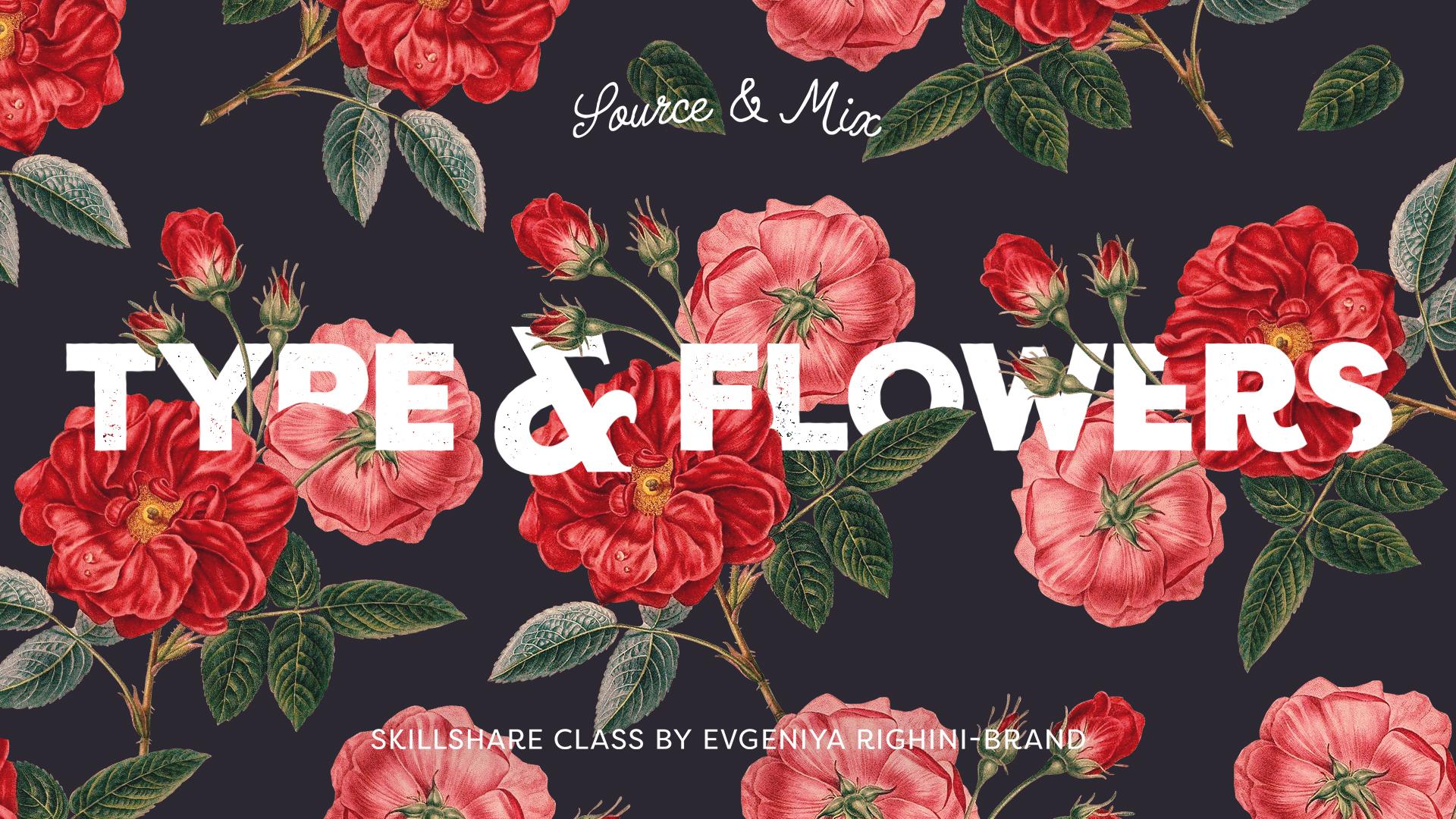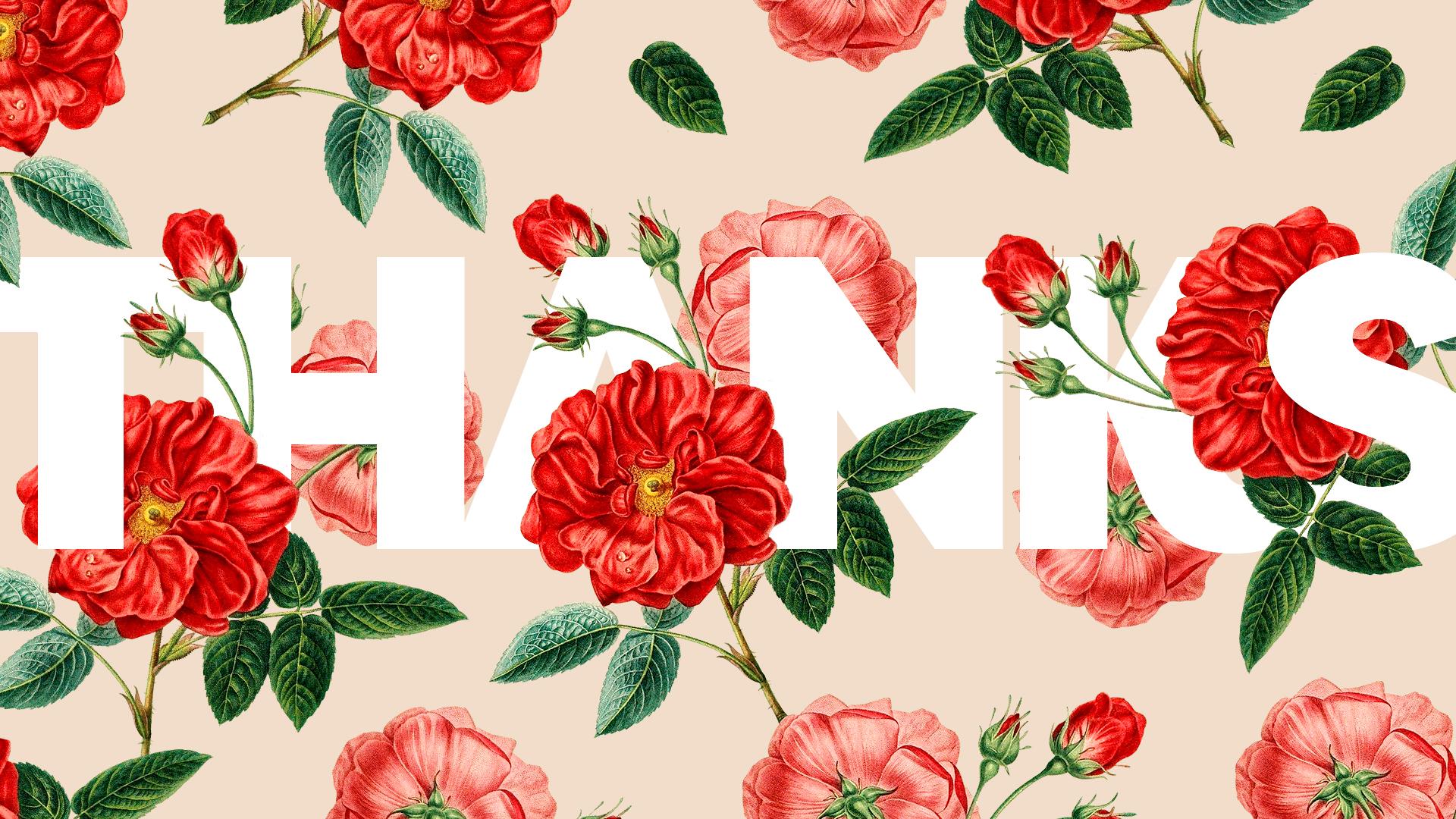
1. Aperçu du cours: Type audacieux et simple combiné avec de belles illustrations florales ou botaniques. Je parie que vous en avez vu beaucoup ces derniers temps sur des cartes, des
vêtements, des articles de papeterie de mariage et des affiches. C' est un moyen très simple mais très efficace de créer des designs
élégants avec un sens de valeur et de sophistication. C' est Eugenia de Attitudes Creative et dans cette classe, je vais passer par le processus de combinaison d'illustrations botaniques vintage trouvées de ce type pour créer des designs captivants qui peuvent être utilisés dans un large éventail de projets, de cartes de vœux personnelles, papeterie de
mariage ou décoration de fête à tout matériel marketing et identité visuelle. Cette classe couvre une nouvelle série de techniques Photoshop telles que l'utilisation des masques de calque, ajustements de
couleur et la toute nouvelle fonctionnalité de type de correspondance Photoshop. Je serai très heureux de voir ce que vous pouvez créer. Rejoignez-moi dans cette classe pour faire quelque chose de branché, pour célébrer l'été et la belle typographie.
2. Approvisionnement et coupe: Avant de commencer, parcourez et trouvez des images inspirantes. Si vous voulez vérifier mon tableau Pinterest, tapez des fleurs pour commencer. Ensuite, trouvez quelques belles images source que vous pouvez utiliser dans votre conception. Tout ce qui est floral ou botanique peut très bien fonctionner dans cette classe. Ça n'a pas besoin d'être une fleur. Il peut s'agir de feuilles, de branches ou de fruits ou de baies. J' aime vraiment l'apparence de cette rose donc c'est ce que je vais utiliser. Je reçois des images de la biodiversité et si vous ne savez pas où trouver des images, consultez la liste des ressources de cette classe, et regardez ma précédente classe sur les collages numériques à partir d'illustrations d'encyclopédie vintage, où j'ai montré un gamme de sources de ces images. Assurez-vous que l'image que vous souhaitez utiliser dans votre conception n'est pas protégée par le
droit d'auteur et téléchargez la plus grande taille disponible. Maintenant, je vais ouvrir l'image téléchargée dans Photoshop et re-enregistrer comme elle est tout de suite dans le dossier source de ce projet. Ce fichier que je vais garder en tant que fichier source. Donc, j'ai toujours le fichier original au cas où j'aurais besoin de revenir en arrière et de faire autre chose avec. Ensuite, je vais le recevoir dans l'autre dossier où je vais garder la découpe. Je vais l'enregistrer au format PSD parce que je voulais de la transparence. Je vais garder le même nom de fichier pour l'instant, et je vais intégrer le profil de couleur et je vais cliquer sur « Enregistrer ». Maintenant, ce que je dois faire est de couper la rose de son arrière-plan. Je vais utiliser l'outil de lasso polygonal. Mais si vous voulez utiliser une autre méthode, vous pouvez le faire. Si vous ne savez pas comment découper les choses, revenez à ma classe précédente sur les collages numériques où je couvre et montre une gamme de différentes façons de découper les choses dans Photoshop. Avant de commencer à couper, je veux dupliquer le calque. Donc, je l'ai juste au cas où et je vais créer une autre couche ici avec une couleur vive afin que je puisse voir comment mes boutures fonctionnent. Maintenant, je vais zoomer assez près et commencer à couper. Lorsque j'ai coupé mon image, j'ai besoin de dupliquer ce calque quelques fois et de séparer quelques éléments sur différents calques pour pouvoir masquer
facilement les choses et utiliser un peu dispersé autour de mon dessin. Je veux donc séparer cette fleur, quelques bourgeons et quelques feuilles. Maintenant, je vais renommer rapidement toutes les couches
afin de pouvoir naviguer rapidement dans mon fichier et l'enregistrer. Après avoir séparé ma rose en éléments séparés, je vais enregistrer ce fichier en tant que fichier maître et je n'y apporterai plus de modifications. Je vais garder le maître dans sa taille d'origine, mais pour cette classe, je veux redimensionner cette image. Donc, je vais aller au menu, taille de
l'image, et je vais changer la résolution à 300 dpi. Je vais continuer à rééchantillonner pour préserver les détails. Je vais changer les unités en centimètres et changer la taille de mon image. Je n'ai pas besoin qu'il soit si grand parce que le design final va être beaucoup plus petit. Je vais donc descendre à 20 centimètres de largeur pour avoir une image de bonne qualité. À ce stade, assurez-vous de ne pas écraser votre fichier maître, mais plutôt d'enregistrer des couches d'éléments individuels sous forme de fichiers séparés. Donc, je vais passer par les calques un par un, supprimant tout ce dont je n'ai pas besoin et en enregistrant chaque élément dans un document PSD distinct. Maintenant, je suis prêt à commencer à travailler sur mon design. Si vous avez plus d'une image source à couper, passez par le même processus, puis passez à l'étape suivante.
3. Agencement des éléments: Après avoir découpé toutes les illustrations que vous souhaitez utiliser dans votre conception, il est temps de commencer à les assembler toutes. Créons un nouveau fichier dans Photoshop. Puisque pour ce projet de classe, nous allons créer une carte de vœux, nous devons le garder à l'esprit lors de la configuration du document. tailles standard des cartes de vœux peuvent varier légèrement d'un pays à l'autre, mais en général, elles conservent quelque part environ six ou cinq points si elles sont grandes ou peuvent être carrées selon le côté le plus long du format A6. Étant donné que nous sommes tous dans différents pays, je suggère que vous décidiez de la taille pour vous-même, fonction de ce qui est utilisé dans votre pays. Je vais accepter les tailles standard A pour l'instant. Je suis généralement assez débrouillard quand je travaille et je pense à l'avance sur la façon dont je peux utiliser ce sur quoi je travaille. Maintenant, sachant que je travaille réellement sur la carte, je vais créer un fichier gratuit à la place afin que je puisse aussi utiliser ce travail pour quelqu'un d'autre. utilisation des formats A est également assez bonne parce que je peux assez facilement l'échelle
proportionnellement mon travail vers le bas pour atteindre la taille A6 désirée de la carte finale. Je vais utiliser le mode couleur RVB parce que je vais télécharger dans mon travail juste société six et c'est ce qu'ils utilisent, mais si vous voulez utiliser CMJN et imprimer votre travail professionnellement, allez-y. Cliquez sur « OK » et sauvegardons ce fichier tout de suite. Je vais le mettre dans mon dossier de développement, le renommer, assurez-vous que ce format NPSD et cliquez sur Enregistrer. Maintenant, je peux commencer à placer ma carte dans ce fichier. Vous pouvez le faire comme vous le voulez, et je vais placer des fichiers liés afin que je vais passer par toutes mes découpes un par un et les placer dans mon document. Assurez-vous de cliquer sur « Entrée » pour placer l'image. J' ai tous les éléments dont j'ai besoin dans un seul fichier. J' ai les règles complètes et tous les éléments individuels en tant que couches séparées. Ils sont tous au même endroit que sur leurs règles d'origine, ce qui sera très pratique à la prochaine étape de masquage. Je vais regrouper tous les éléments individuels et les cacher parce que je n'en ai pas besoin pour le moment, puis je vais commencer à travailler sur la composition globale de la carte. Les rôles sont en fait assez petits par rapport
au format global et c'est bon car il sera plus facile masquer les choses sinon le type serait
trop caché par les éléments de la rose ou vice versa. En termes de composition globale, vous pouvez faire ce que vous voulez. Vous pouvez avoir un seul élément sur un fond coloré, vous pouvez avoir une image de taille supérieure si vous formater est comme
ça ou vous pouvez dupliquer vos images et les disperser sur toute la toile. Vous décidez de l'apparence de votre carte. Ça a l'air sympa. Maintenant, je veux changer l'arrière-plan. Je vais aller chercher quelque chose de gentil et [inaudible], qui fonctionnera bien avec ces fleurs pour l'instant, et j'y reviendrai plus tard dans tous les cas pour finaliser mon design. Vous pouvez utiliser tous les raccourcis de suppression pour remplir le calque avec la couleur de premier plan définie dans le panneau Outils ou utiliser l'outil de seau de peinture. Maintenant, je peux commencer à penser à comment je peux ajouter du type à cette composition.
4. Ajout d’un type: Retournez à votre recherche et décidez de l'écriture que vous voulez avoir sur votre carte. Ça peut être n'importe quoi. Vous pouvez inclure seulement quelques mots pour définir l'ambiance. Vous pouvez utiliser un devis. Vous pouvez écrire, félicitations, joyeux anniversaire ou merci. Vous pouvez écrire le nom ou les initiales de quelqu'un. C'est à vous de décider. Je vais aller pour quelque chose de simple et polyvalent. Maintenant, je dois rendre ma typographie agréable. La première chose que je vais faire est en fait de définir la couleur de mon texte, quelque chose que je peux bien voir et travailler avec, mais ce n'est peut-être pas la couleur finale que je vais utiliser tout de suite. Ensuite, j'ai besoin de choisir de belles polices de caractères ou polices de caractères. Si vous n'êtes pas très confiant de travailler avec le type, consultez ma première classe dans la série de topographie de mastering, qui couvre les principes de base de la création de compositions typographiques visuellement attrayantes, sélection et l'appariement de polices de caractères, et les paramètres disponibles dans les panneaux de caractères et de paragraphes. Comme tous ces trucs sont couverts là-bas, je ne vais pas entrer dans le sujet de cette classe. Alors dirigez-vous vers ma classe, le guide des débutants pour créer designs
étonnants pour plus d'informations sur le travail avec le type. Pour ce projet, je voudrais
avoir une police assez simple qui créera un joli contraste avec une illustration très détaillée. Vous pouvez remarquer que si vous regardez mon type de planche de fleurs sur Pinterest, la
plupart des compositions comportent des polices sans serif audacieuses, et dans la plupart des cas, il est également mis en blanc. Ce n'est pas surprenant parce que le blanc permet d'
ajouter plus d'air et de sophistication dans la composition, et de le rendre assez doux et élégant. Donc, si c'est ce que vous voulez faire en termes de style, allez-y. Si vous utilisez le type comme je l'ai fait, il y a beaucoup de polices de caractères à ces fins là. Alors amusez-vous. En outre, si vous avez la dernière version de Photoshop, il y a une nouvelle fonctionnalité impressionnante là-bas, qui est appelée police de correspondance. Cette fonctionnalité vous permet de faire correspondre les polices trouvées dans n'importe quelle image ou photo à votre bibliothèque de polices et aux polices disponibles via Typekit. Alors, voici comment ça marche. Disons que vous aimez l'aspect de la police sur cette image, mais vous ne savez pas quelle police il s'agit et vous ne
savez pas si vous avez quelque chose de similaire dans votre bibliothèque. Ouvrons cette image dans Photoshop. À l'aide de l'outil de sélection rectangulaire, sélectionnez la police que nous voulons identifier. Ensuite, allez au type de menu, faites correspondre la police. Là, vous verrez la liste des polices d'apparence similaire qui peuvent être trouvées dans votre bibliothèque ou sont disponibles pour synchronisation via Typekit. Vous pouvez déplacer la sélection ou la redimensionner pour sélectionner différentes zones et voir comment la liste des polices change. C' est une toute nouvelle fonctionnalité dans Photoshop, et il n'est pas parfait, et il peut vous donner quelques allumettes assez sauvages. Mais en général, cela peut être un point de départ cool. Donnez-lui un coup d'envoi et partagez votre expérience si vous le souhaitez. Si vous souhaitez utiliser l'une des polices de votre conception, synchronisez-la à partir de Typekit, sélectionnez dans la liste et cliquez sur « OK ». Maintenant, vous pouvez commencer à taper avec elle et voir à quoi elle ressemble par rapport à la police d'origine dans l'image. En utilisant la fonctionnalité de police de correspondance, j'ai trouvé cette police vraiment agréable, qui est en fait très différente de la police de caractères dans l'image, mais j'aime vraiment son apparence, en particulier la lettre R. Je pense que cela fonctionne très bien avec ces roses. Je vais l'utiliser de deux façons différentes pour ajouter un peu de contraste et de sophistication à la composition. Maintenant, je vais rapidement taper ceci et le placer à peu près où je veux qu'il soit. Ça a l'air assez bien. Maintenant, je suis en mesure de le développer davantage en ajoutant un peu de volume à ma composition en masquant des parties du type.
5. Travailler avec des masques: Après avoir défini mon type et la position sur l'illustration, ce qui est bon pour cacher certaines parties de type derrière l'illustration, je peux commencer à travailler sur l'ajout d'un volume imaginaire à mon design. En regardant l'image, je peux analyser quels éléments sont plus proches et ce qui peut être considéré comme plus éloigné. Je peux également utiliser les découpes d'images séparées de ce groupe pour m'aider à comprendre sur quel plan imaginaire je veux mettre mes textes et quels éléments je peux avoir devant lui et quels éléments vont certainement être derrière lui. Si vous avez des éléments plus petits dans vos illustrations florales ou botaniques, vous aurez plus de liberté en masquant les choses que moi. Je ne veux pas cacher des lettres au point
qu'elles soient méconnaissables et d'un autre côté, je ne veux pas trop détruire les fleurs. Alors je vais commencer et me décider à mesure que j'y vais. Je vais cacher le groupe avec les éléments individuels pour l'instant et je reviendrai sur eux quand et si j'en ai besoin. Maintenant, j'ai besoin d'ajouter un masque de calque à mon calque de type. J' ai donc besoin de sélectionner le calque de type dans le panneau Calques et de cliquer sur ce bouton ici. Les masques de calques sont un moyen extrêmement utile et
non destructif de masquer des parties du calque ou de mélanger différents calques ensemble, si vous travaillez avec une manipulation de photomontage ou de photos. En outre, si vous le souhaitez, vous pouvez utiliser des masques de calque pour découper des éléments lorsque vous traitez des collages. Ainsi, les masques contrôlent l'opacité du calque auquel ils sont appliqués. zones blanches du masque de calque sont opaques. couleur noire sur le masque rend la couche transparente et les nuances de gris créent différents niveaux d'opacité. Vous pouvez sélectionner la couleur dans le panneau Outils et peindre dans différents niveaux de transparence à l'aide de l'outil Pinceau. Quel que soit le mode de couleur de votre document, 100 % de blanc serait 255 dans les trois canaux RVB et le noir sera trois zéros. Vous devez vous assurer que vous travaillez avec 100 % noir et 100 % blanc si vous voulez avoir une transparence totale ou une opacité totale. Sinon, vous aurez différents niveaux de transparence, ce qui est utile dans certains cas, mais certainement pas dans cette classe. Pour qu'il soit plus facile de masquer certaines parties de MyType derrière les éléments de la fleur, j'ai besoin d'aller au premier calque
sur lequel je veux construire mon masque et de cliquer sur sa vignette dans le panneau Calques. Maintenant, le contenu du calque est sélectionné, et je vais pouvoir utiliser cette sélection pour peindre dans la transparence sur le masque. Ensuite, je dois sélectionner le masque de type dans le panneau Calques. Assurez-vous que la couleur de premier plan est définie sur noir. Zoom-in de près afin que je puisse voir tous
les détails et en utilisant la brosse dure de la taille appropriée, peignez les parties que je veux apparaître derrière les feuilles. À ce stade, je peux également utiliser mes éléments pré-découpés pour le
rendre plus rapide pour sélectionner différents bits comme celui-ci à partir de la fleur. Donc, je vais faire une sélection à partir de sa forme et la peindre sur le masque ici. Quand j'en ai fini avec la sélection, je dois aller faire une sélection à partir autre illustration que je veux être devant mon type. Je dois le faire avec tous les éléments que je veux couvrir mon type. Si je veux que mon type soit masqué par les petits éléments l'illustration comme ce morceau de pétale, par exemple, je masquerais rapidement le calque de type et en utilisant l'outil Lasso polygonal, sélectionnez la pièce que je veux masquer. Révélez ensuite le calque de type, sélectionnez le masque et la peinture dans la sélection. Vous pouvez également le faire en diminuant l'opacité du calque
de type et en utilisant l'outil Pinceau pour suivre les lignes de l'illustration. Mais ce n'est peut-être pas aussi précis que l'utilisation de l'outil Lasso polygonal. Lorsque vous avez terminé de masquer les choses,
regroupez toutes vos images dans le panneau Calques et assurez-vous d'enregistrer le fichier. L' étape suivante consiste à finaliser les couleurs.
6. Développement de variantes de couleurs: Vous aimeriez peut-être déjà ce que vous avez fait, mais à ce stade, c'est toujours une bonne idée de développer votre travail et d'essayer différentes variantes de couleur. Pour ce faire et pour préserver l'œuvre d'origine, si vous disposez de la dernière version de Photoshop CC, vous pouvez utiliser des plans de travail. Si ce n'est pas le cas, vous devrez enregistrer des fichiers individuels pour chaque version. Je vais rapidement vous aider à travailler avec Artboard dans Photoshop. le panneau Calques, sélectionnez le calque d'arrière-plan qui définit la taille de votre travail, puis accédez à Menu Calque,
Nouveau, Plan de travail à partir des calques. Cela permet de rassembler tous vos calques visibles dans un dossier Plan de travail du panneau Calques. Vous pouvez désormais dupliquer votre plan de travail autant de fois que vous le souhaitez, la même manière que vous copieriez un calque, sorte que vous pouvez créer une version couleur différente de votre plan sur un plan de travail distinct. Il existe également un outil Plan de travail dans le panneau Outils qui vous
permet de travailler avec la taille, la position et les paramètres du plan de travail. Ne soyez pas trop fou avec un certain nombre de plans de travail car ils augmenteront la taille de votre fichier. gardez-le gérable et assurez-vous d'enregistrer votre travail au fur et à mesure que vous apportez des modifications. La première chose que vous pourriez vouloir modifier est la capacité de votre type. Avoir une couleur unie est agréable, mais baisser la capacité à 90, 80 ou 70 pour cent, peut faire une grande différence à son apparence. J' aime tout à fait ce mouchoir ou papier
calque regarder parce qu'il rend l'ensemble du design plus léger et plus aéré. prochaine chose facile à faire est de jouer avec la couleur de fond et de voir comment elle affecte la perception globale de votre design. J' aime utiliser la couche de réglage de la saturation de la teinte pour modifier la couleur de l'arrière-plan, car de cette façon je peux voir les changements que j'applique en temps réel et je peux toujours l'éteindre si je le veux. Vous pouvez également utiliser la saturation de la teinte pour ajuster les couleurs de l'illustration ou la colorier dans une illustration ici, vous pouvez la faire affecter uniquement aux illustrations en liant le calque de réglage au groupe, ou vous pouvez lui faire des illustrations d'effet et l' arrière-plan en plaçant le calque de réglage ici, ou vous pouvez le faire affecter l'ensemble du tableau en plaçant le calque de réglage au-dessus de tous les autres contenus du dossier Plan de travail. Vous pouvez également obtenir un effet très agréable en utilisant l'ajustement de la carte de dégradé. Placez-la dans le panneau Calques où vous souhaitez être par rapport à l'image et liez-la à ce que vous voulez appliquer, puis jouez avec les couleurs du dégradé. Cliquez sur le dégradé pour ouvrir la fenêtre Éditeur de dégradé, puis choisissez un dégradé dans les paramètres prédéfinis ou définissez vos propres couleurs en cliquant sur les arrêts de couleur et en sélectionnant les couleurs dans le sélecteur de couleurs. Deux couleurs sont très belles, mais si vous voulez en avoir plus, vous pouvez ajouter plus d'arrêts de couleur à votre dégradé. À ce stade, vous pouvez également ajouter d' autres réglages tels que la luminosité et le contraste ou les niveaux. Lorsque vous êtes satisfait des résultats, enregistrez le fichier PSD de développement,
puis allez dans Fichier de menu, Exporter les plans de travail vers les fichiers. Ici, vous pouvez exporter des plans de travail individuels en tant que fichiers PSD distincts, ce qui peut être utile si vous voulez aller plus loin dans une version spécifique, ou vous pouvez exporter des plans de travail individuels pour impression ou Web et être fait avec elle. Si vous souhaitez créer une carte pliable pour l'impression, exportez les plans de travail vers PSD Files avec les paramètres, et passez à l'étape suivante de la préparation de votre conception pour l'impression en tant que carte de vœux pliée.
7. Préparation de l’impression et conclusion: Si vous voulez imprimer votre carte et la rendre pliable, il y a quelques choses que vous devez faire. Ouvrez le fichier PSD, que vous souhaitez utiliser pour la carte,
puis accédez à l'image du menu, à taille de l'
image et à la réduction de l'échelle de votre travail. Par exemple, je veux avoir une carte A6 et il y a un préréglage pour cela. Je vais également changer la méthode de rééchantillonnage pour bicubique plus nette, ce qui est préférable pour la réduction de la taille. Cliquons sur « OK ». Puisque la carte doit être pliable, nous devons y ajouter le dos. Allons dans le panneau Calques et dissocions le contenu de nos mots d'art. Cliquez sur Commande Shift G plusieurs fois pour que nous puissions voir toutes nos couches comme il se doit. Regroupez maintenant toutes les images et les textes. Si des ajustements sont appliqués à l'ensemble de l'image, veillez à garder le calque de réglage en dehors de ce groupe. Commande maintenant cliquez sur la « vignette de calque d'arrière-plan », puis sélectionnez votre groupe dans le panneau Calques et ajoutez un masque de la sélection à elle. Vous ne voyez pas encore de changements, mais vous verrez pourquoi je le fais dans un instant. Maintenant, allez à beaucoup d'image taille Canvas, puis si vous avez une carte verticale comme je le fais, définissez l'ancre vers la droite en cliquant sur cette flèche et doubler la largeur. Si vous avez une carte qui s'ouvre le long du bord horizontal à la place, réglez l'ancre en bas et remontez la hauteur, cliquez sur « OK ». Donc, c'est l'édition de retour. Maintenant, vous pouvez voir que j'ai ajouté le masque pour masquer les éléments qui sont en dehors de la partie avant. Bien sûr, à ce stade, vous pourriez réellement vouloir enlever le masque et
les ramener ou même ajouter d'autres illustrations à l'arrière, c'est à vous de décider. Je veux juste que la couleur de fond couvre entièrement à l'arrière de ma carte, donc je vais rapidement le redimensionner. Vous pouvez également ajouter votre nom ou votre logo ou quelque chose d'autre à l'arrière, alors optez pour le si vous le souhaitez. On dirait qu'on est presque là, mais je veux faire encore une chose. Que vous imprimiez à la maison ou à l'imprimerie, il est conseillé d'avoir des marques coupées pour couper votre imprimante à la taille finale. C' est une façon professionnelle de faire les choses parce que de cette façon vous pouvez couper à la taille désirée et laisser de la place à l'erreur. Vous ajoutez des lames, qui seront coupées, ce qui garantit que le bord de votre impression semble parfait, surtout si votre impression dépasse le bord comme dans mon cas. Ajoutons des lames et des marques de rognage. Photoshop ne facilite pas les choses, donc nous devrons le faire manuellement. Si vos règles sont masquées, révélez-les en cliquant sur Commande R ou Ctrl R dans Windows, puis faites glisser les repères hors de celles-ci et alignez-les sur les bords de votre Canvas. Si vous avez activé la capture, cela facilitera la tâche. Accédez à de nombreux snapshots de vue et assurez-vous qu'il est activé. Ajoutez également un guide vertical au centre de votre toile ou un guide horizontal si votre carte s'ouvre d'une manière différente. Maintenant, allez à l'image du menu, Taille de la
toile, s'assure que l'ancre est réglée au centre, changer les unités de deux millimètres et ajouter six ou 10 millimètres à la fois la largeur et la hauteur, cliquez sur « OK ». Maintenant, nous devons étendre notre image dans la zone de la lame, afin de redimensionner l'arrière-plan avec un outil de transformation gratuit, puis sélectionnez la face avant de la carte du bord au centre, sélectionnez le masque et remplissez la sélection avec une couleur blanche. Peu importe que ça n'ait pas l'air équilibré parce que c'est la partie que nous allons couper de toute façon, c'est notre lame triée. La dernière chose que nous devons faire est d'ajouter des marques de coupe ou de coupe. Les marques de recadrage vont normalement légèrement au-dessus du bord. Allons à la taille de l'image du menu Canvas à nouveau et ajouter cinq millimètres supplémentaires de chaque côté. Créez à présent un nouveau calque vide au-dessus de tous les autres calques
et, à l'aide de l'outil de sélection rectangulaire, dessinez une sélection entre les arêtes et les repères comme ça. Ensuite, faites un clic droit sur la sélection et dans ce menu sélectionnez « Stroke », Réglez la largeur sur 0,5 points et définissez la couleur sur noir. Alignez le trait vers l'extérieur et cliquez sur « OK ». Ensuite, faites la même chose avec les trois autres coins. À ce stade, vous pouvez également ajouter des repères de pliage. Lorsque vous avez les quatre coins et la commande de crédit de marque complète cliquez ou cliquez sur
Ctrl dans Windows sur la vignette du calque d'arrière-plan pour définir la sélection. Inverser la sélection en maintenant Command Shift I ou Ctrl Shift I dans Windows. Sélectionnez le calque avec les repères de rognage dans le panneau Calques et ajoutez-y un masque de calque. Enregistrez ce fichier en tant que PSD, converti en clé C away si nécessaire, et enregistrez-le au format PDF pour l'impression et placez-le dans le dossier d'impression. Maintenant, vous pouvez imprimer votre carte à l'aide d'un joli papier ou papier cartonné plié selon les repères de pliage. Coupez les lames à l'aide d'une règle et d'un couteau artisanal pour le scalpel et donnez-la à quelqu'un de spécial. C' est tout pour ce cours. J' espère que vous l'avez apprécié et appris quelque chose de nouveau. Si vous avez aimé ce cours, veuillez laisser un commentaire afin que plus de gens puissent le découvrir. Je serai très excité de voir vos cartes. Publiez votre travail dans la section projet pour cette classe et si vous allez partager votre travail sur Instagram, s'il vous plaît prendre des attitudes compétences pour que je puisse le voir là-bas aussi. Si vous avez des questions, laissez un commentaire sur le conseil communautaire pour cette classe, et je serai heureux de répondre et de fournir des commentaires. Merci de vous inscrire à ce cours, et j'espère vous voir dans mes autres cours.